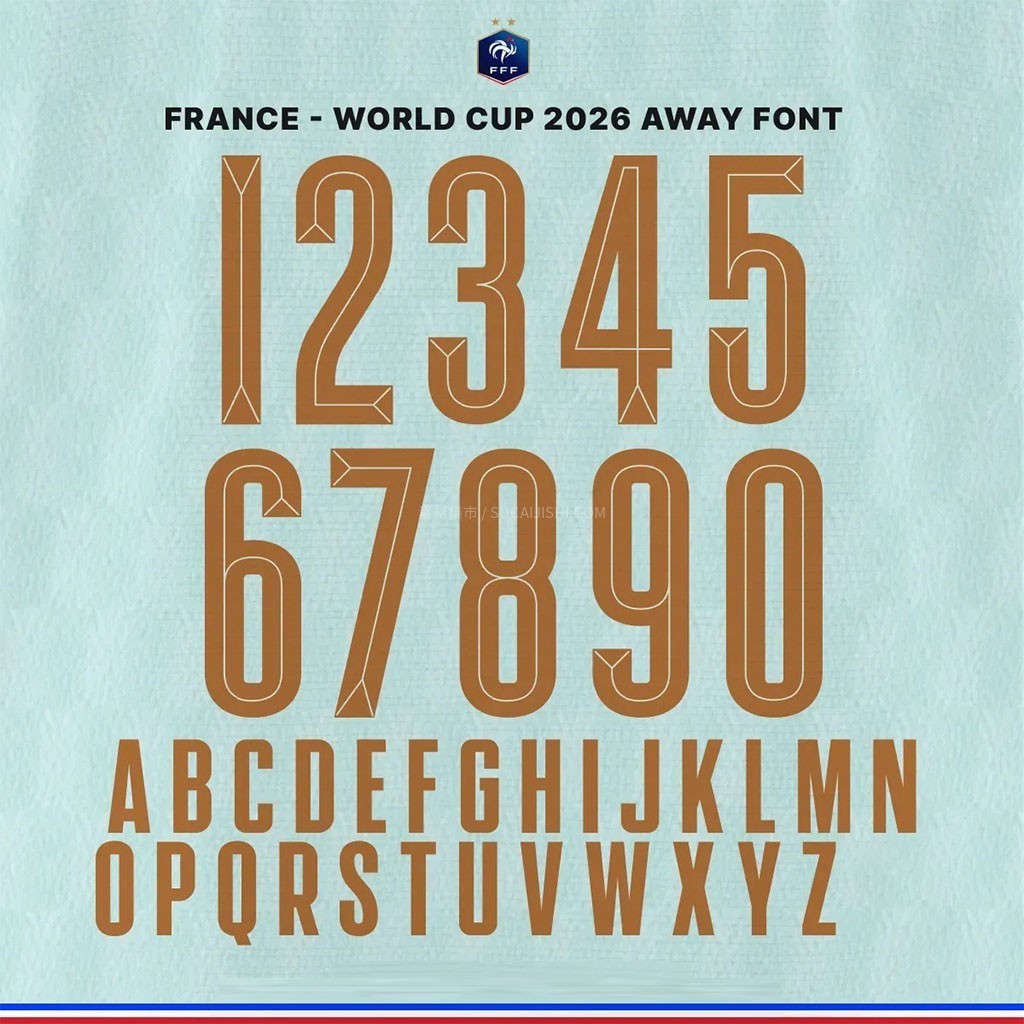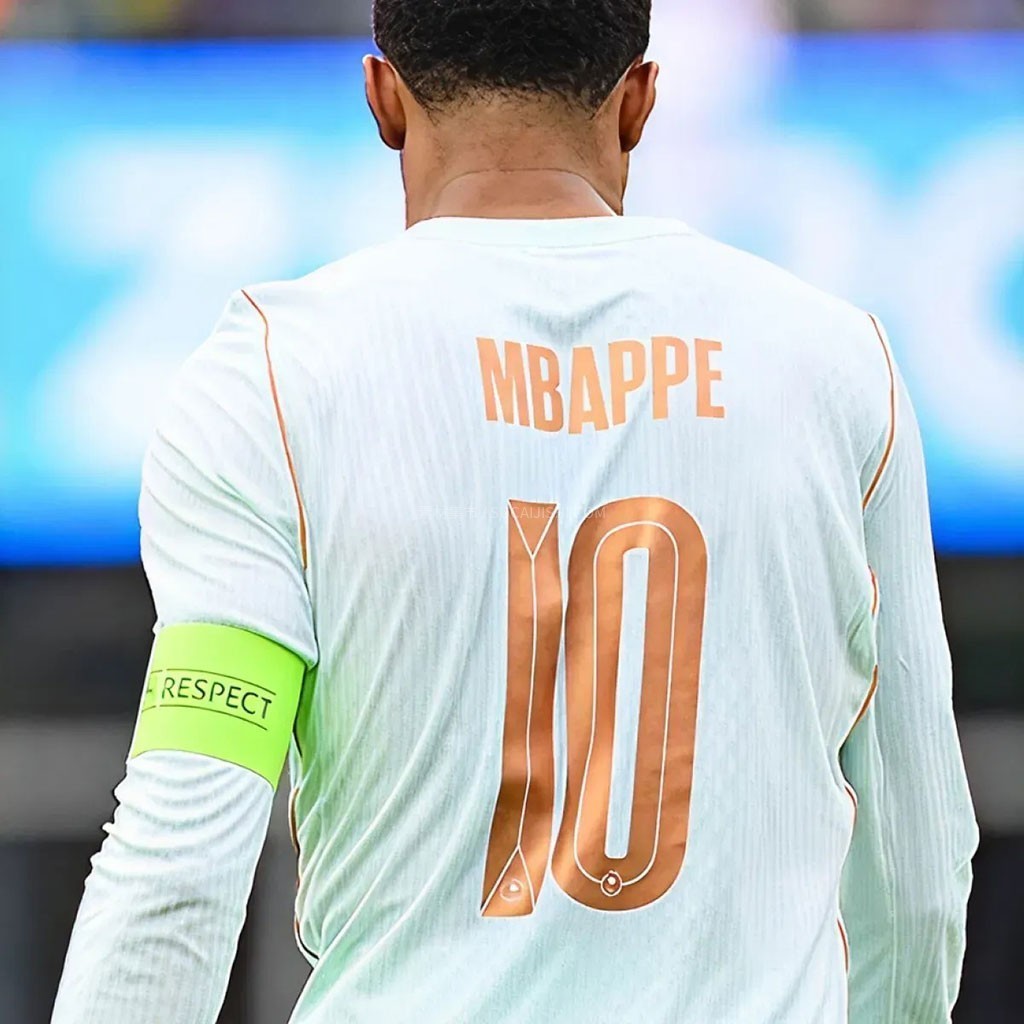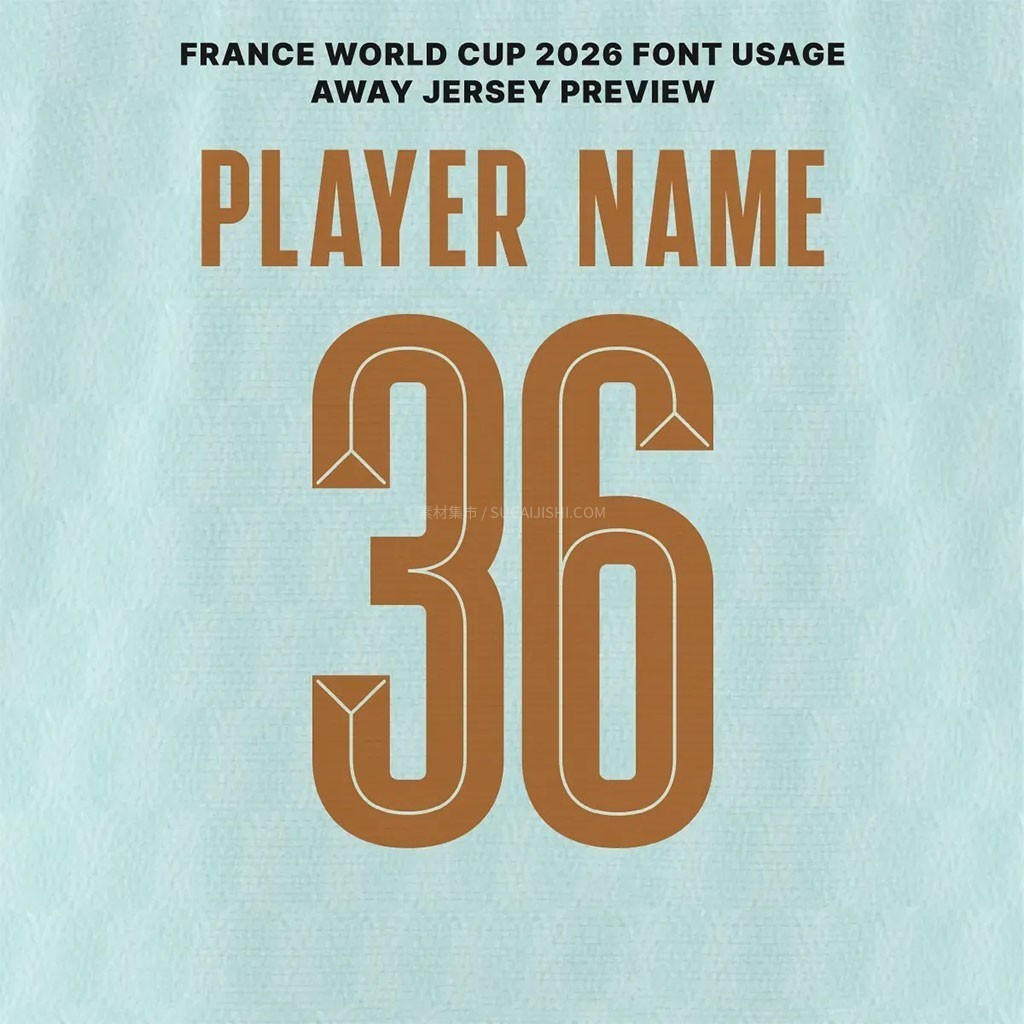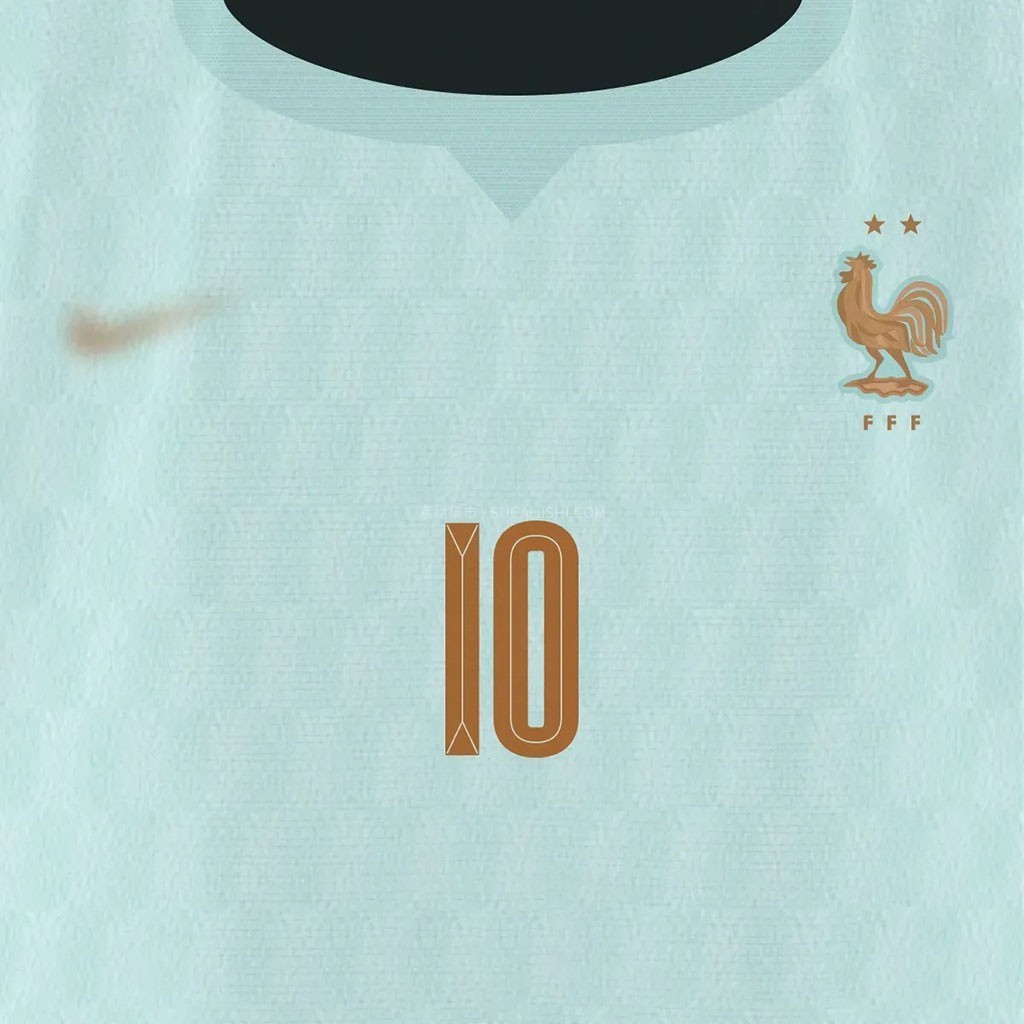
法国2026世界杯客场球衣字体
这款专为法国队2026年世界杯客场球衣设计的专属字体,采用粗体、挺拔且紧凑的字型结构,完美兼顾了远距离的清晰易读性与近距离的高级质感。每个字母都拥有强烈的垂直线条与简洁的笔画末端,深度契合了球衣“自由”(Liberté)的整体设计理念,尽显内敛优雅的法式风情,是提升体育类视觉设计质感的绝佳选择。